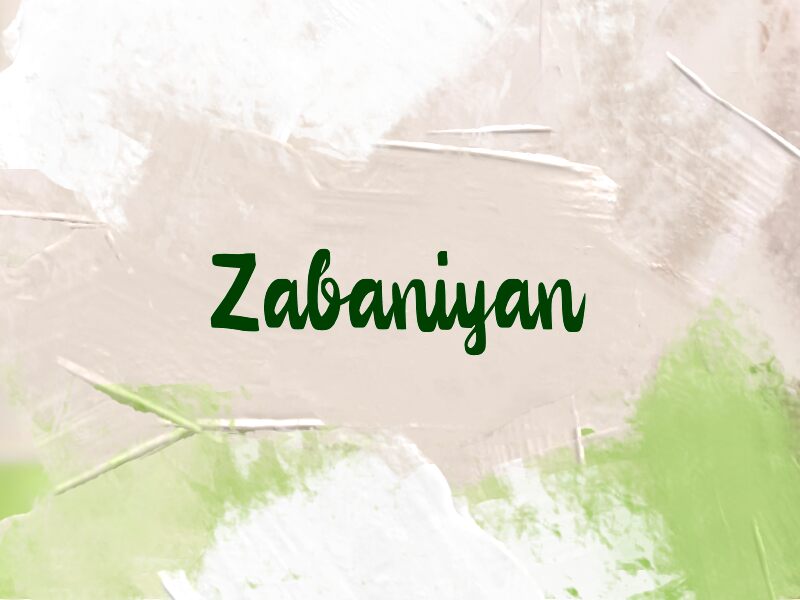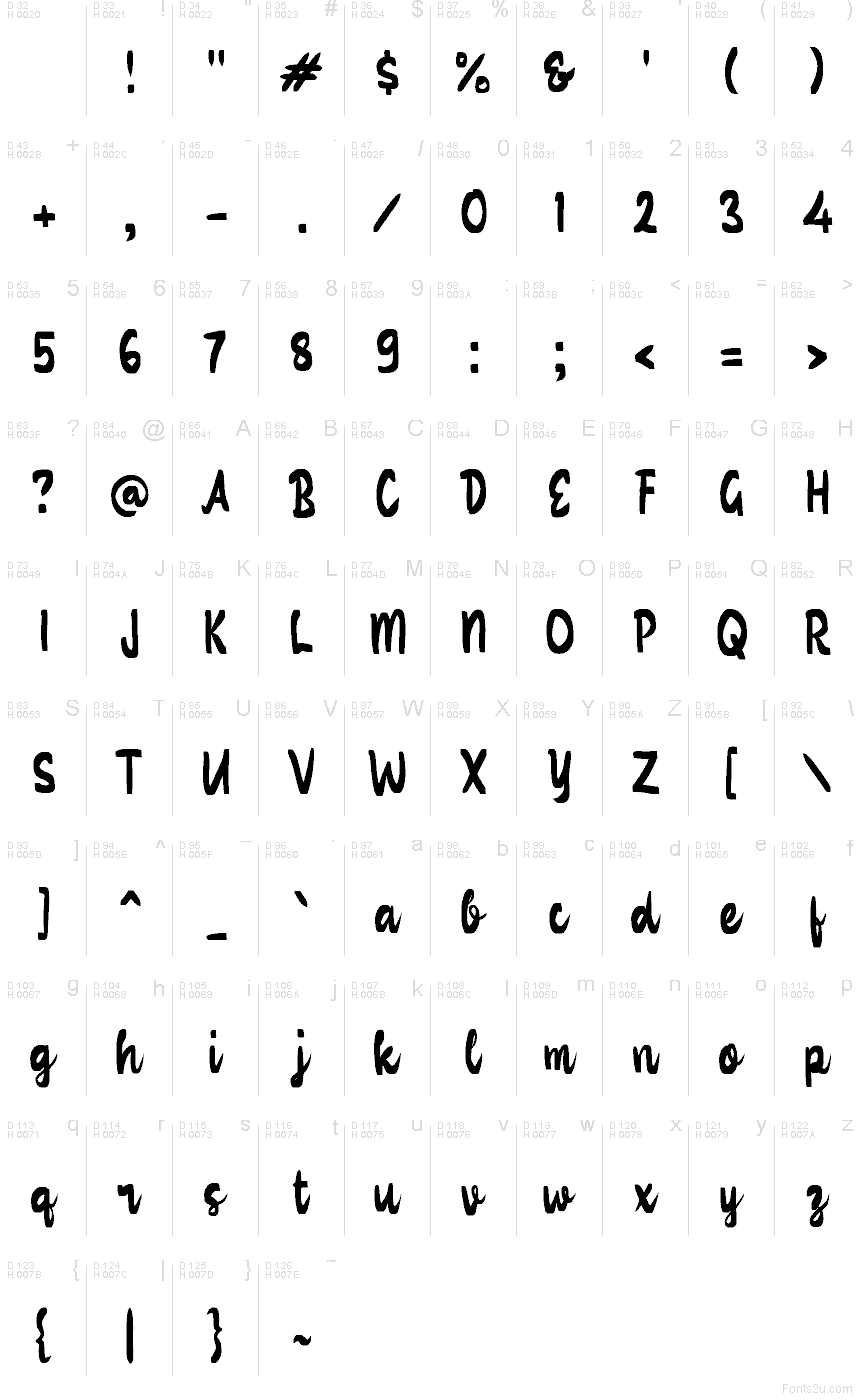
Zabaniyan от Wep — это бесплатный рукописный шрифт с ритмом «под кисть», живыми, размашистыми линиями и насыщенными чернильными штрихами. Буквы выглядят энергично и естественно: мягкие соединения, плавные изгибы и высокие петли придают надписям динамику, напоминающую стиль постеров.
Этот шрифт отлично подойдет для брендинга кофеен, streetwear-брендов, музыкальных обложек, упаковки и заголовков в соцсетях — везде, где требуется бесплатный шрифт, сочетающий непринужденность и характер. Используйте его для коротких заголовков, титров или набросков логотипов, если хотите добиться эффекта надписи, нанесенной одним движением кисти, а не прорисованной по линейке.
Zabaniyan